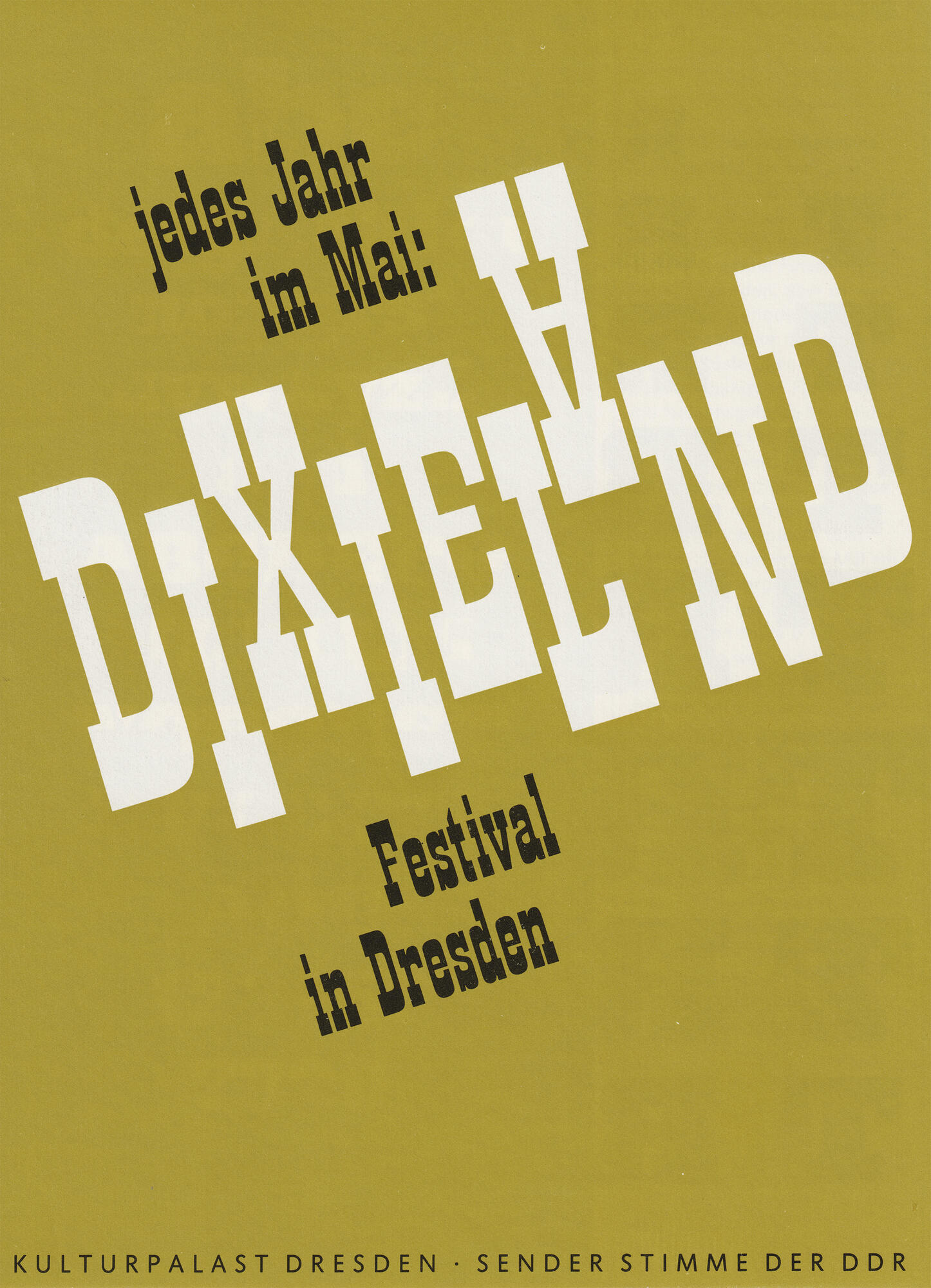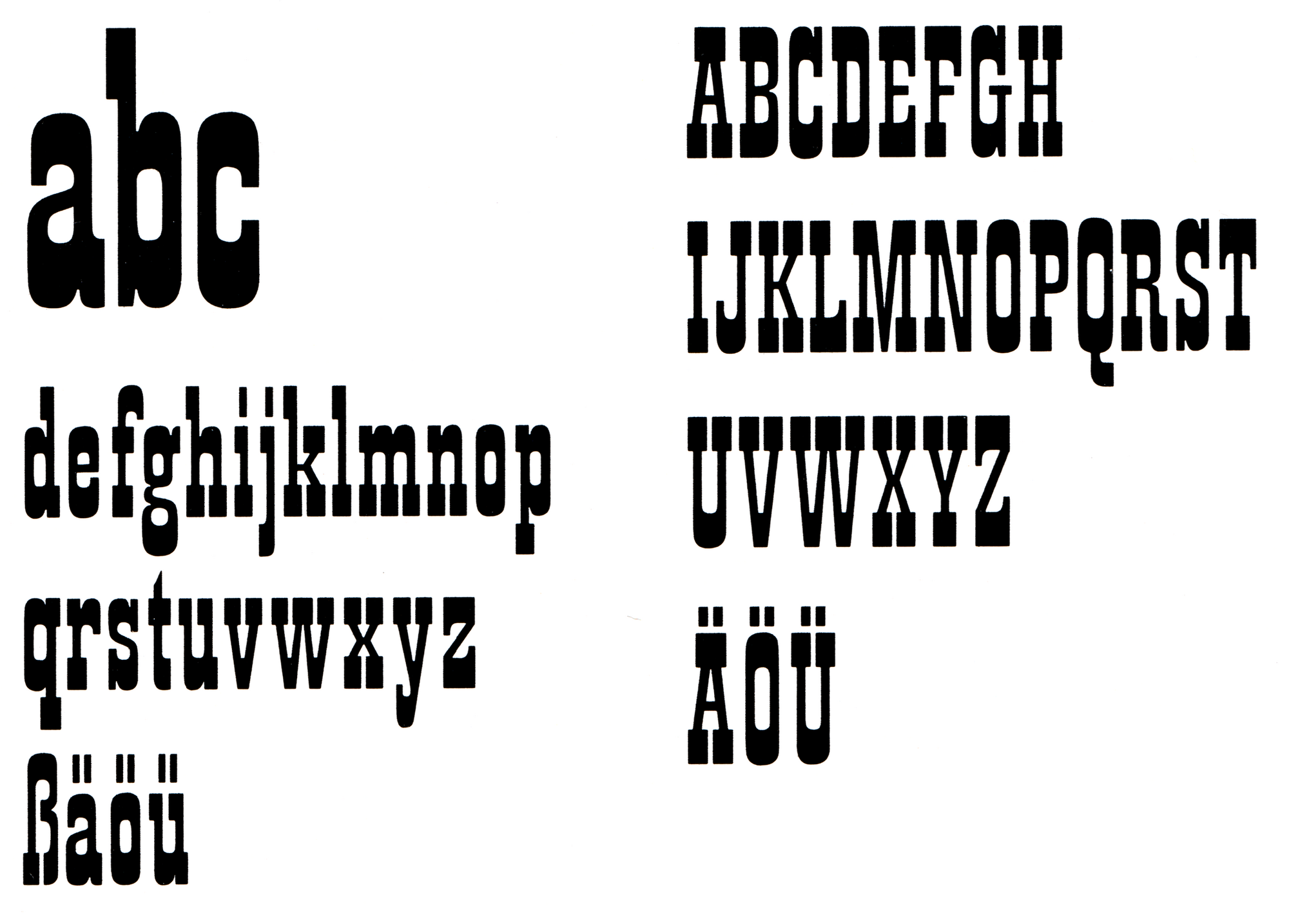
Die Nidor von Harald Brödel erschien Ende der 1980er-Jahre als Fotosatzschrift im VEB Typoart Dresden. Grundlage war eine Italienne-Schrift aus dem Bestand von Schelter & Giesecke.
Elsner+Flake hat die Schrift in zwei optischen Größen digital verfügbar gemacht.